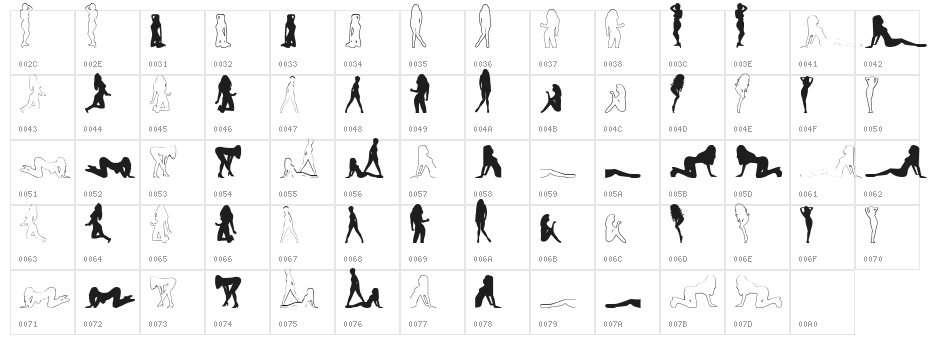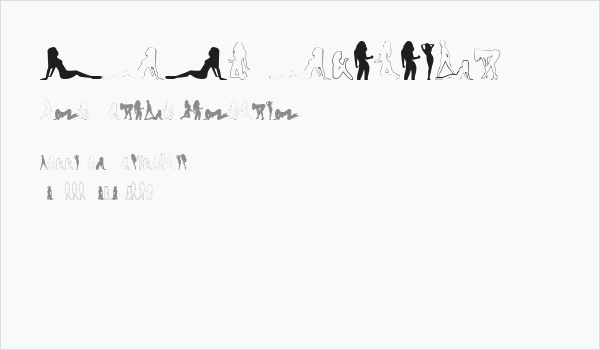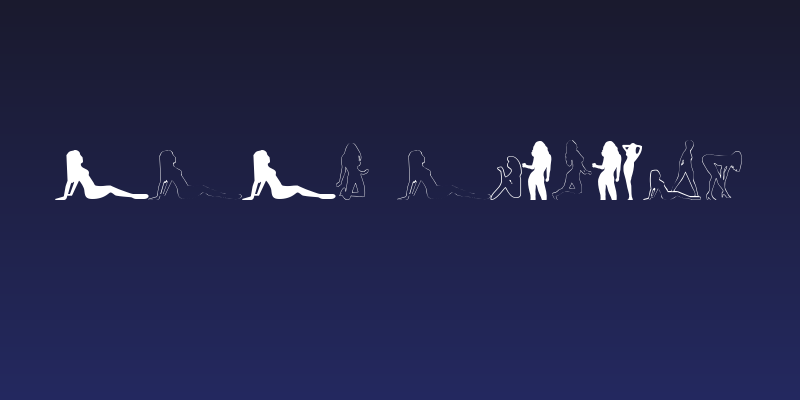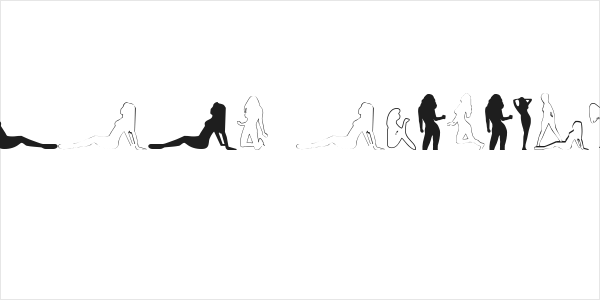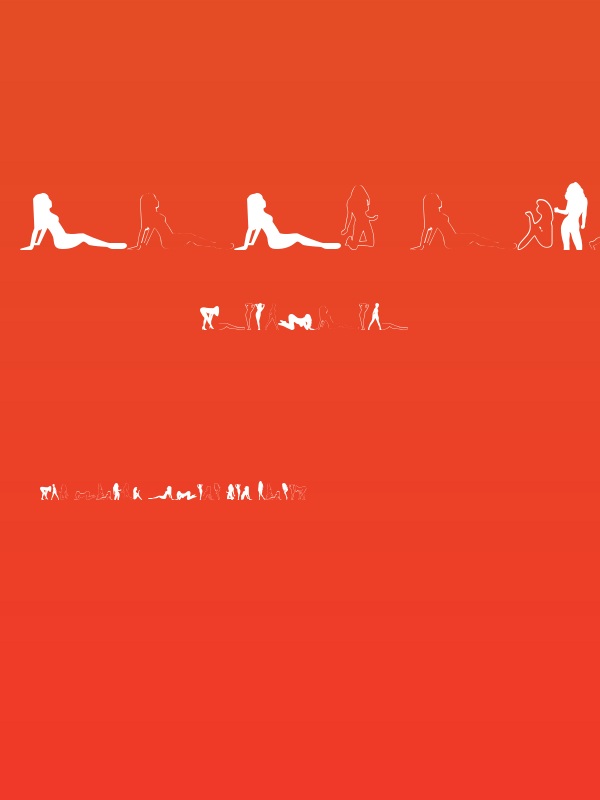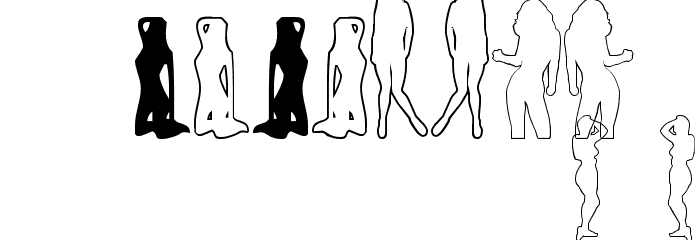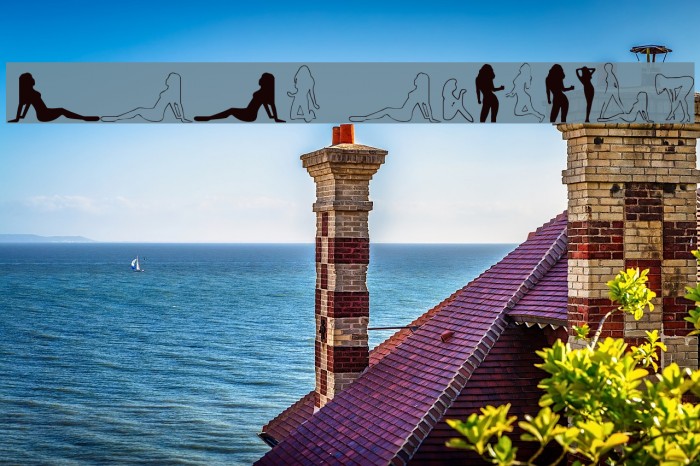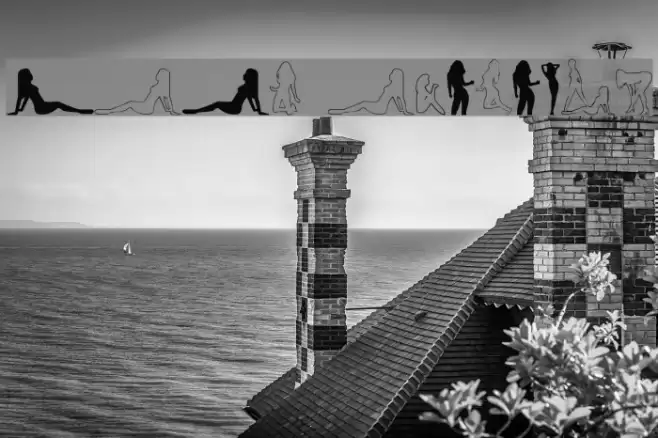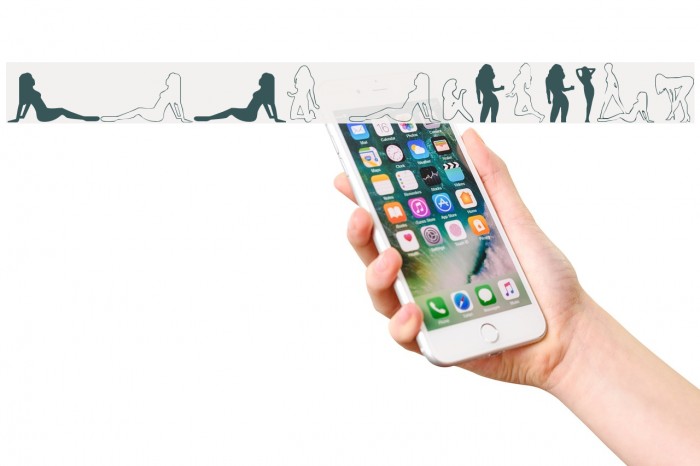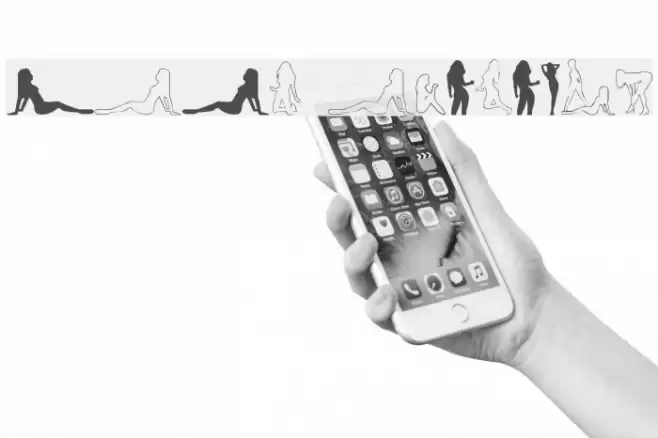
Babe-alicious Font
| Stile generale | Artistic, Creative, Bold |
| Caso d'uso | Logos, Posters, Artistic Projects |
| Progetti proposti | Ideal for artistic posters, creative branding, unique invitations, and any project that seeks to stand out with a bold visual statement. |